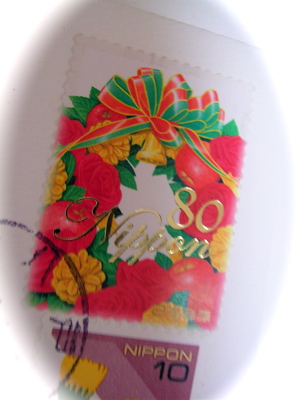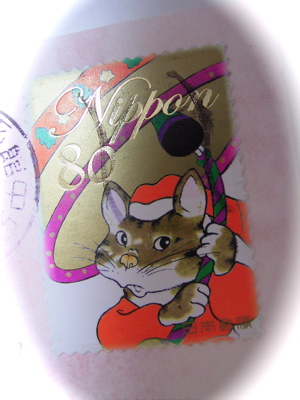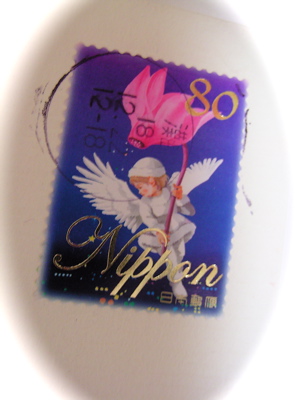
holiday stams
お正月から少しさかのぼりますが、クリスマスの切手の話題です。
日本の切手は印刷技術が優れているので色が美しいと評判ですが、このホリデイシーズンではいつもデザインでは不満足。
海外ではこの季節用の切手のデザインはいろいろで、羨ましい限りです。今年はどんなのが来たのでしょう、
左はオランダから届いたもの。雪の結晶は良いモチーフですよね。シンプルでいいなぁ。確か日本でもありましたよね。
でも確かに色はきれい。Nipponという文字もカリグラフィックなので、そこはちょっと嬉しいかも。
このシリーズは、シール式になっているシートの切手だったかもしれません。
このふたつもそうですね。にゃんこのサンタ、かわいいけどね〜。
宗教的なデザインは無理なのかもしれませんが、もう少し大人っぽい色とかデザインが欲しいですよね〜。みんなそう思うでしょう〜?
年賀状用だけでなく、ホリデイ用も発売して欲しいですよね。
民営化されたら、違うかしら。期待しましょうかね〜・・・・